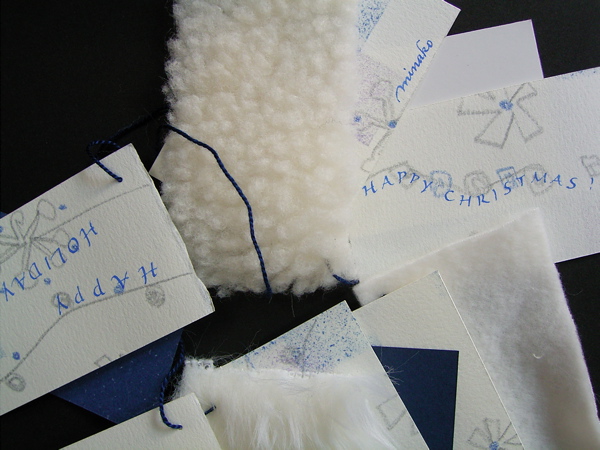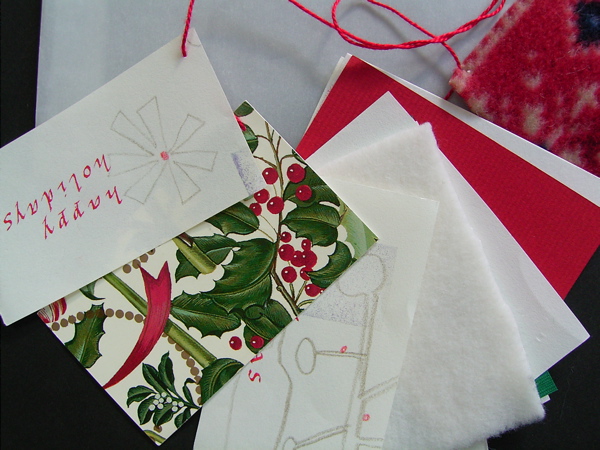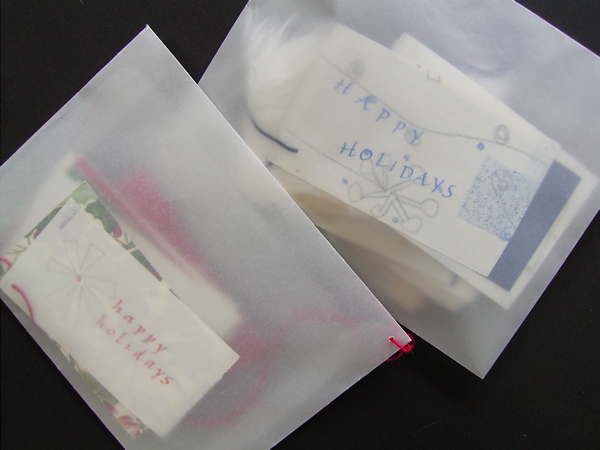
今年のクリスマスカード
まずやらなければいけないのはクラスで作るクリスマスカードのデザインです。今年はこんな感じになりました。
あったか系にしたいなぁ〜と漠然に思っていましたが、新宿のオカダヤに行ってフリースやボアの生地を見つけて今年のデザインは決定!文字を見るだけでなく感触も楽しんで頂きます。
どうしても多くの色を使いたくなる所をなるべく抑えてシンプルに・・・・。封筒はトレーシングペーパーにして中身を見せる様にしました。長い糸がくちゃくちゃに見えるところが可愛いです。
ボアもフリースもと欲張ったら厚くなってしまって、普通の形の封筒では膨らみ過ぎ!でもこんなマルマルとした封筒が家の郵便箱の中にいたら、ちょっとワクワクしますよね。
実は白状しますと、これ、山本デザイン事務所さんから頂いた移転の通知の形が余りにも可愛かったのでパクってしまったのでした。ゴメンナサーイ!